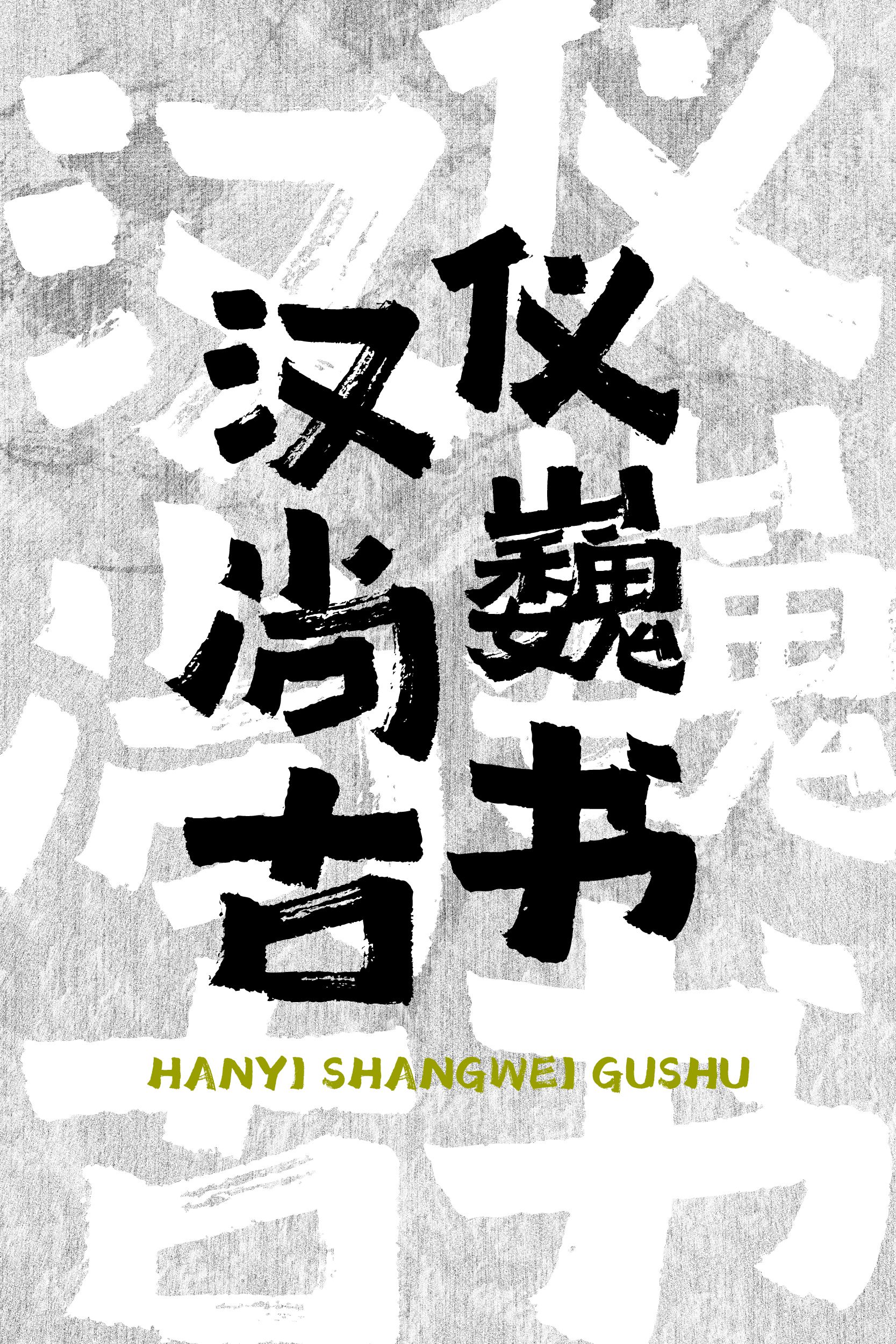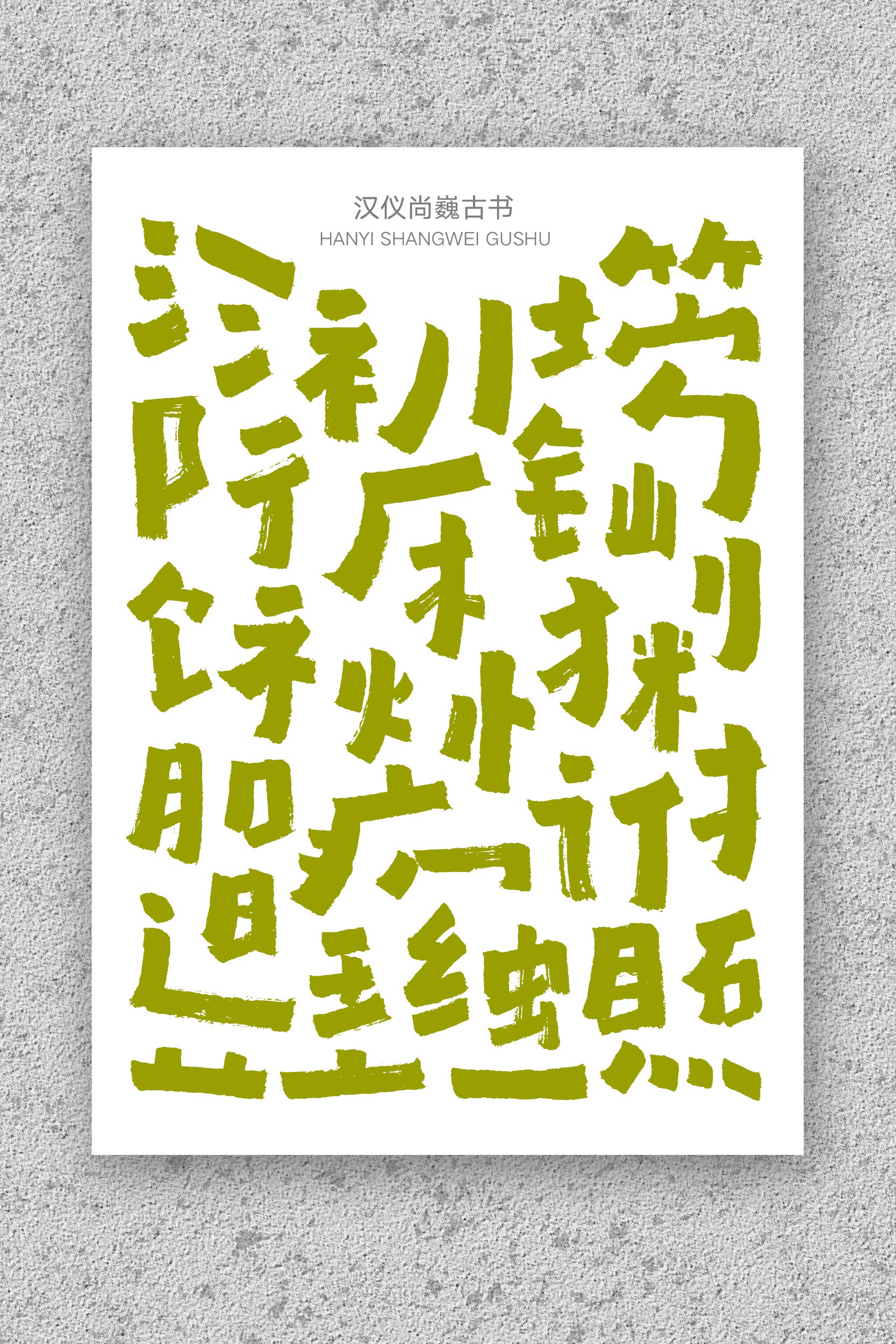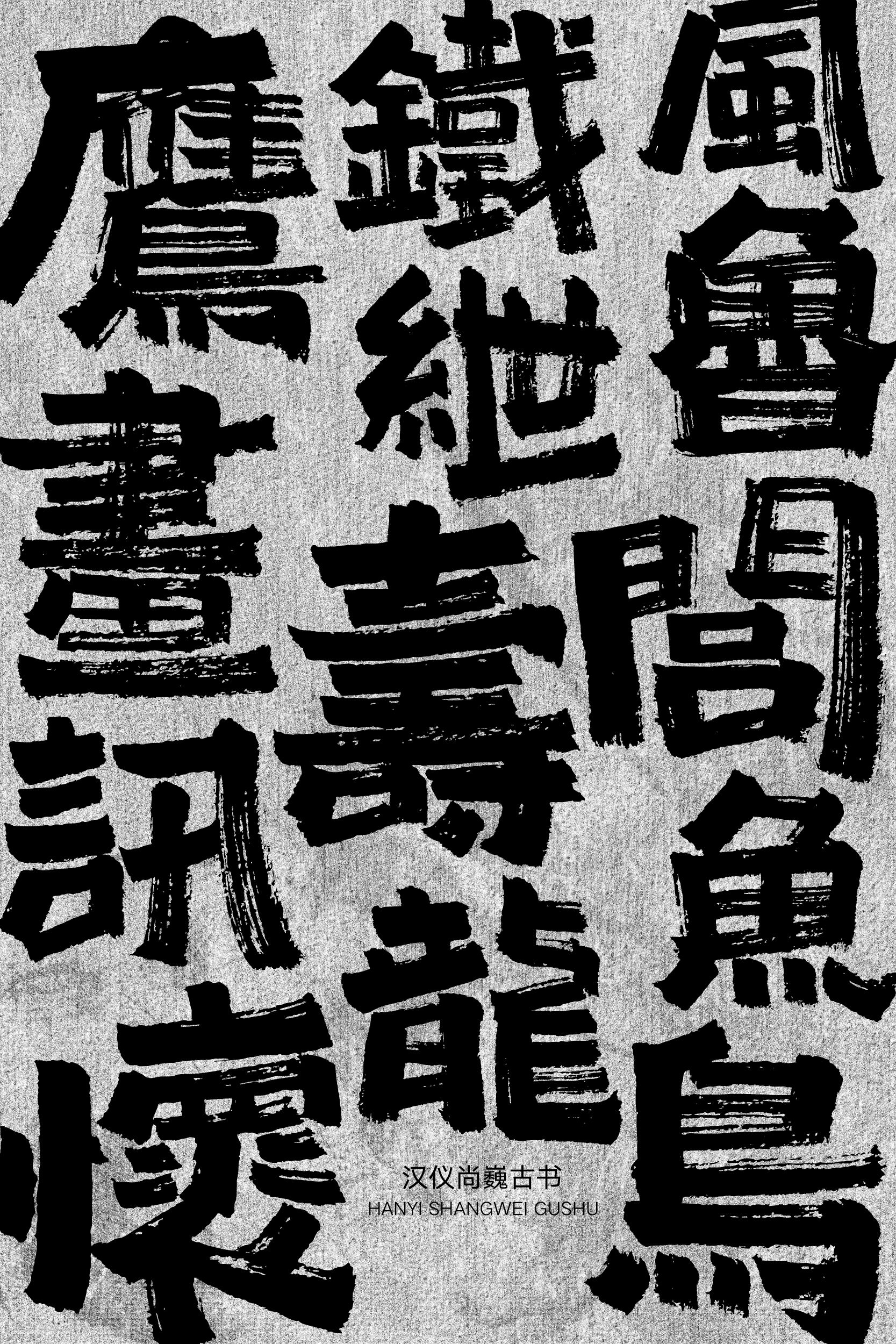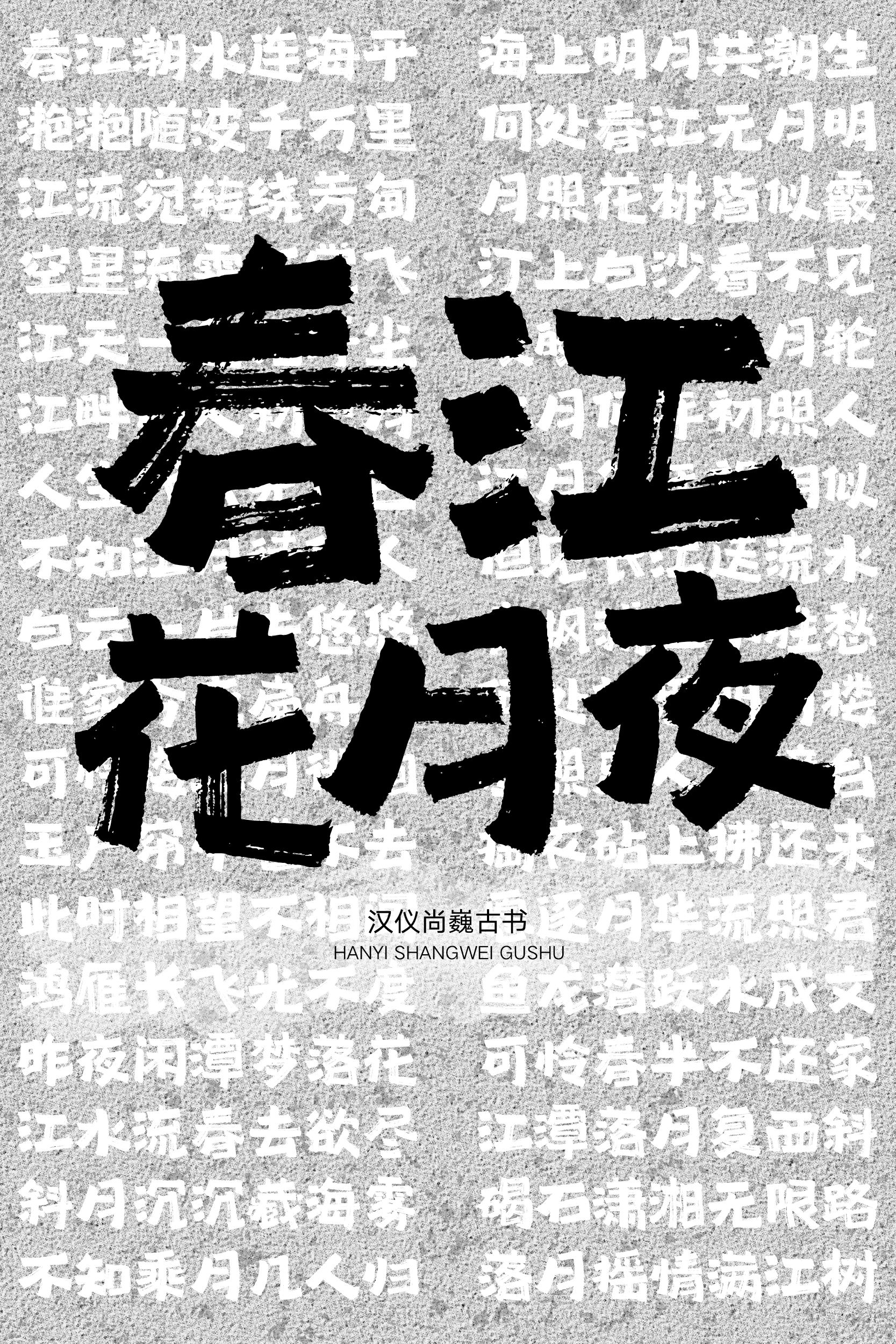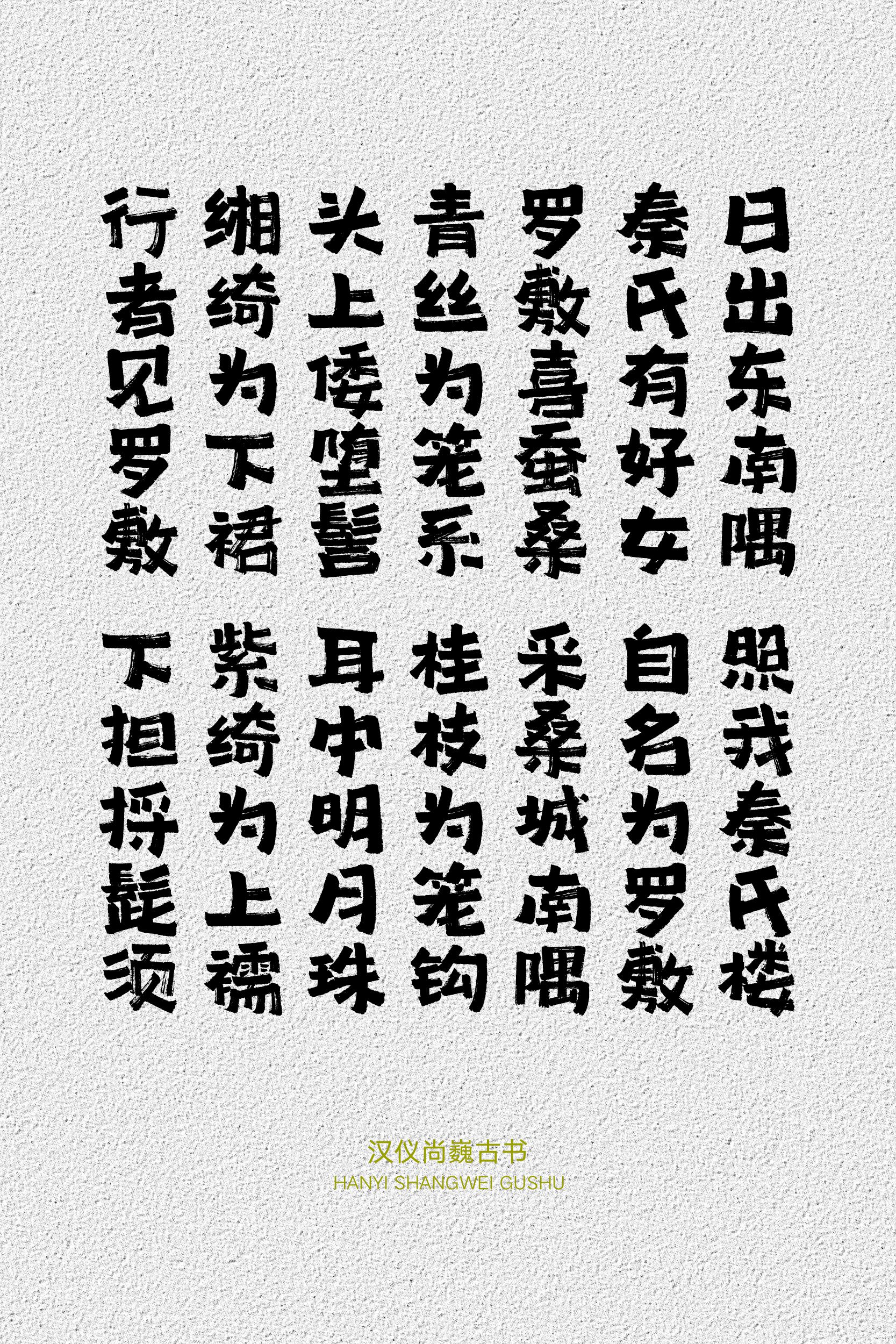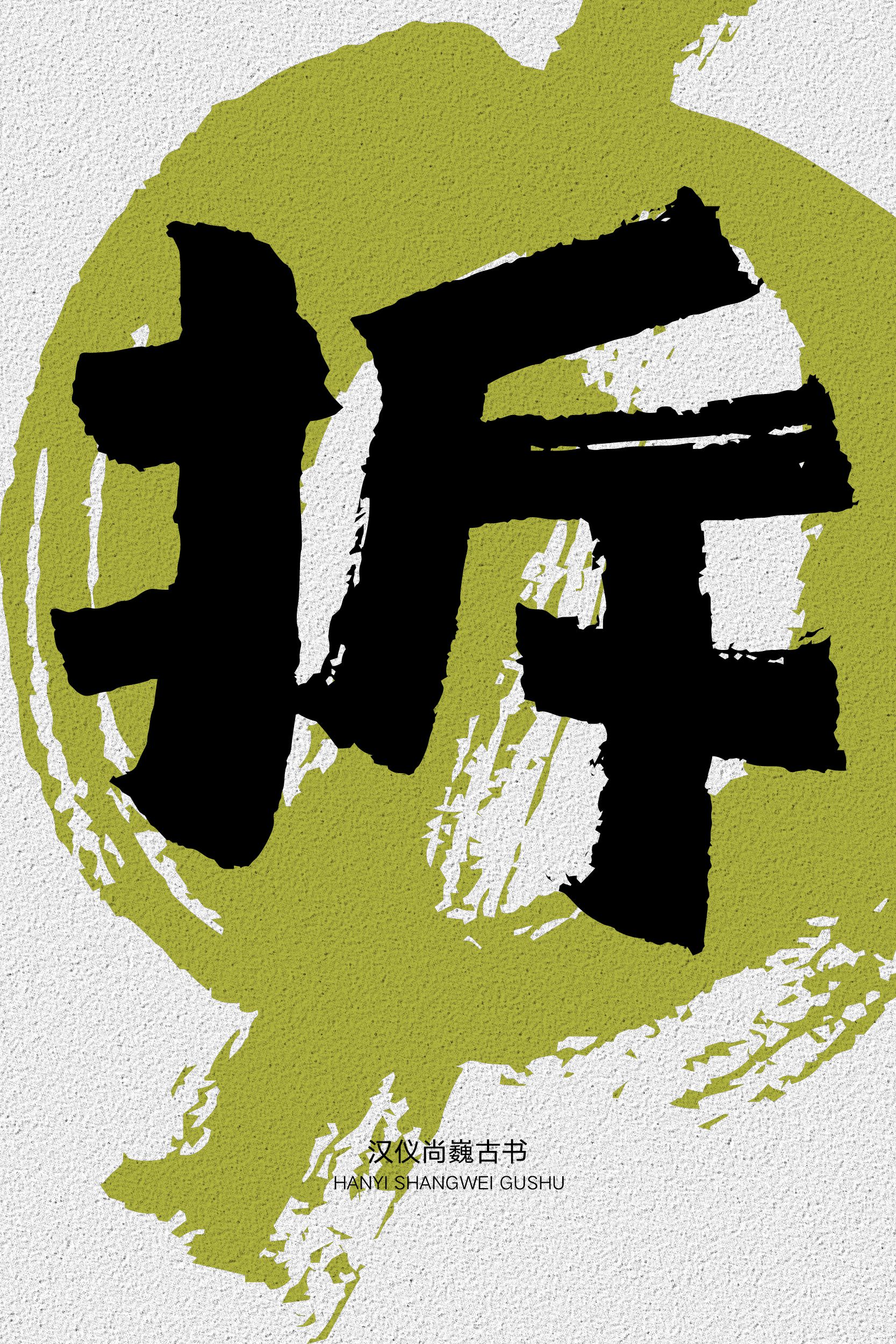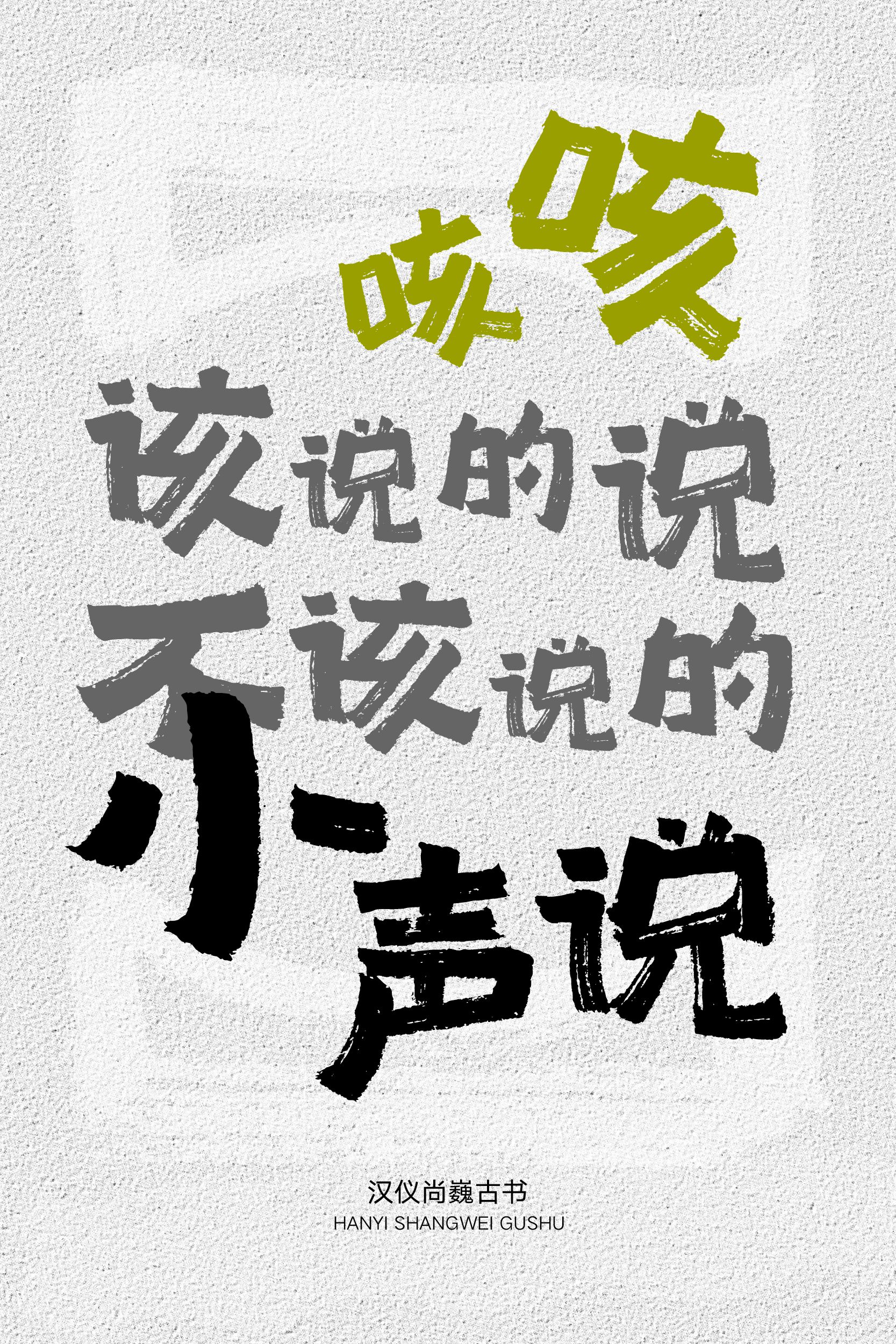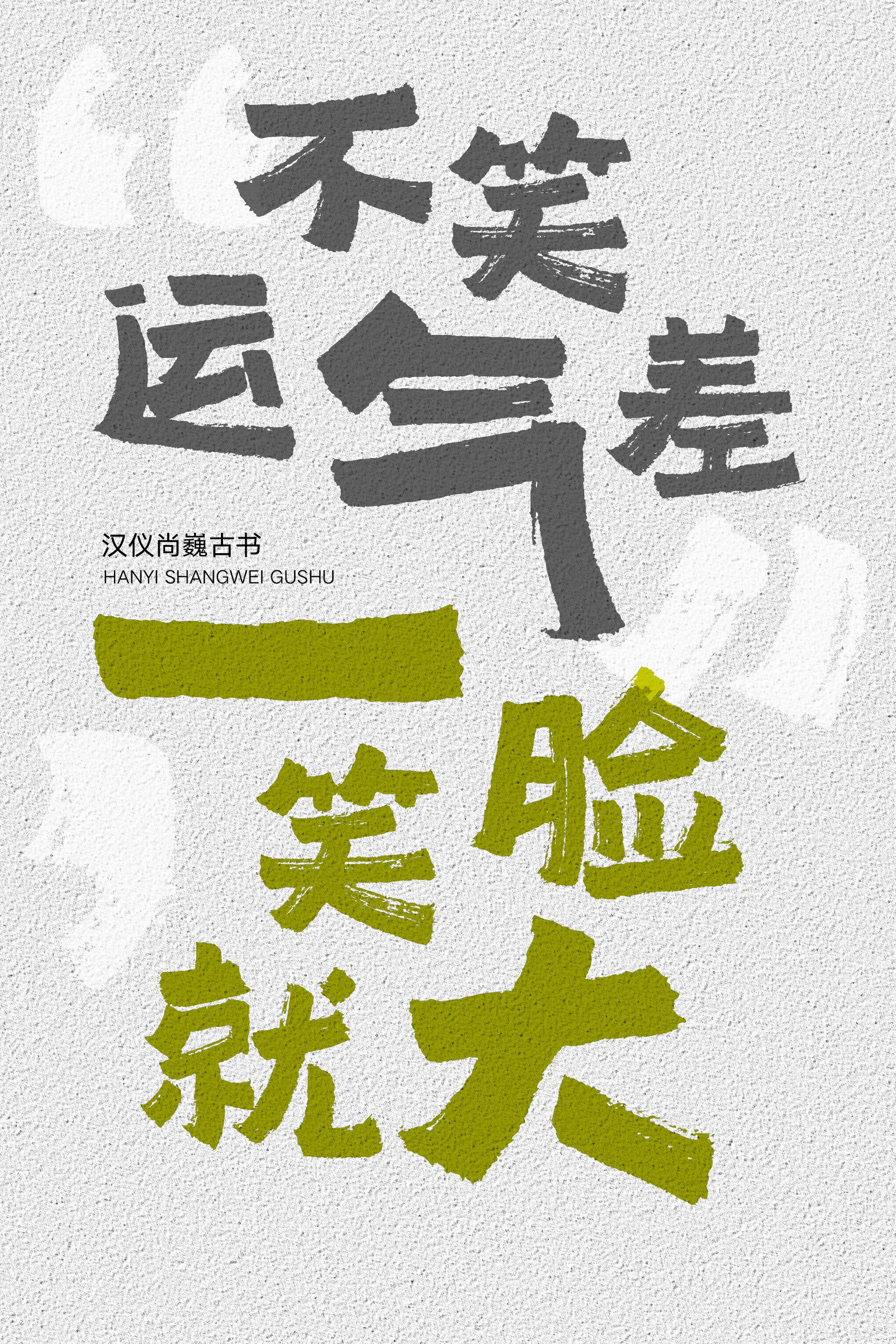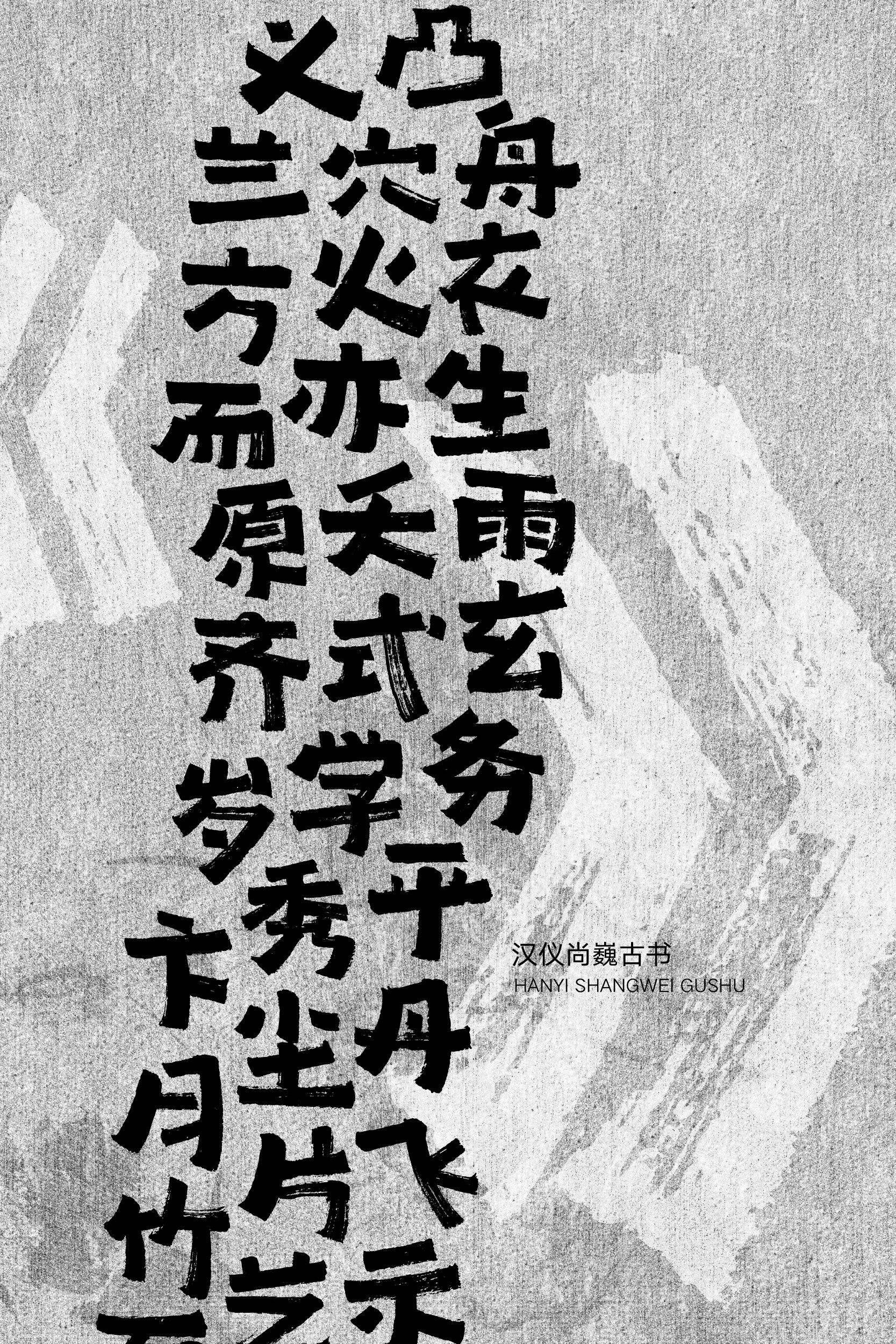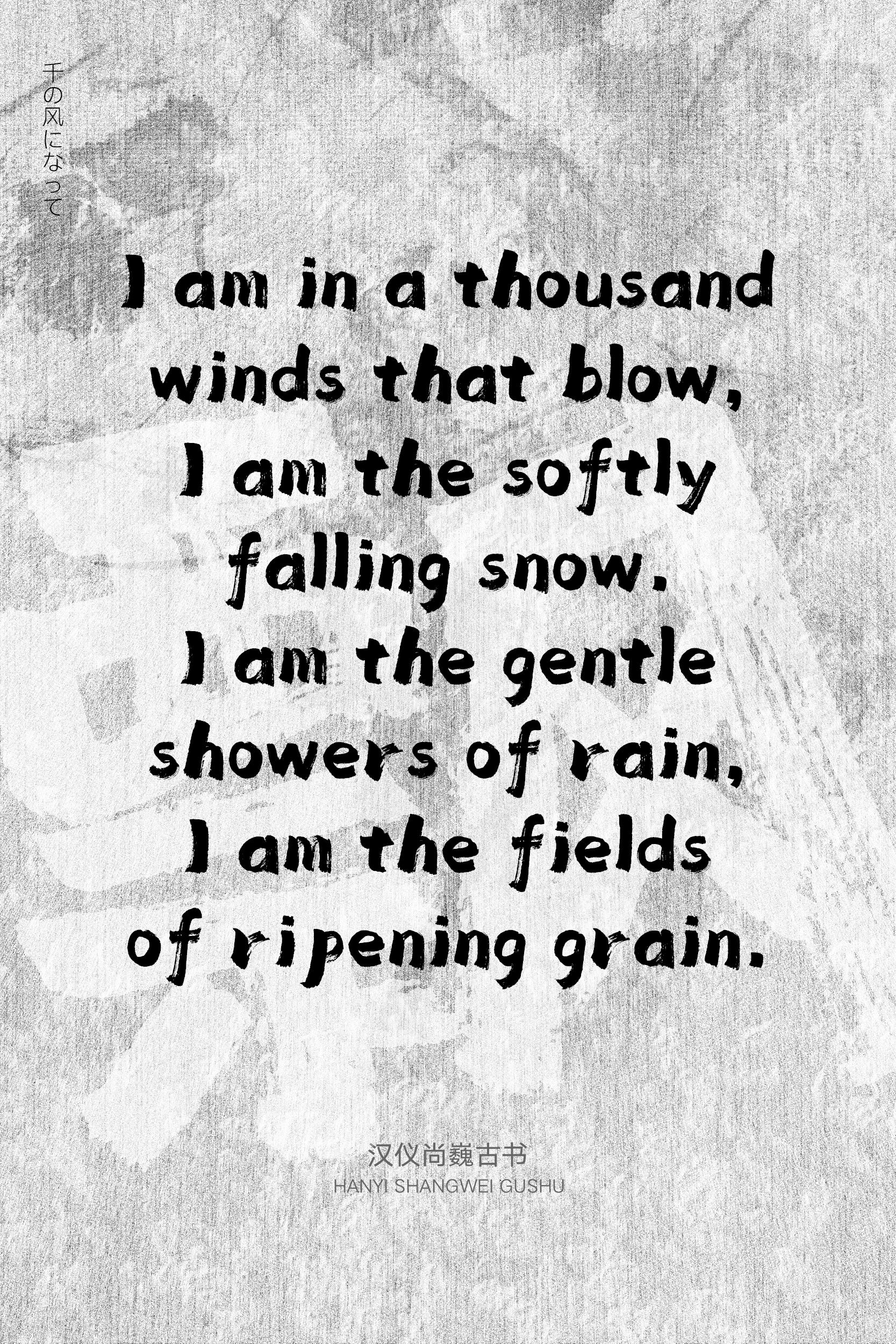
一款可以传递情感的书写字体
书写字体
书写 / 古拙 / 轻松 / 趣味
标志 / 书籍 / 广告 / 杂志 / 动漫 / 游戏 / 影视 / 包装
汉仪尚巍古书是汉仪字库签约作者尚巍创作的一款书写字体,保留书写飞白,视觉效果朴实柔和而寓于拙趣。这款字体既可以用于标题字体,也可以用于较短文案的排版,适用于各类美食、娱乐、休闲场景,传递着醇朴可靠的情感。
字形扁方,左收右放,排版效果齐整有序又不失趣味。
用排刷书写的汉仪尚巍古书笔法遒劲,打破常规的匀称均衡,有坚实、朴茂、稚拙之古趣。
笔画方而粗厚,保留笔刷自然朴拙的书写感,带有飞白。
汉仪尚巍古书的西文部分同样保留了带有质朴书写感的方笔,字形轻松,颇有古拙之趣,与中文搭配排版效果和谐。